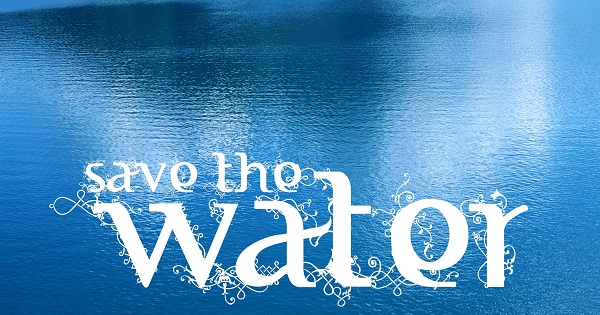
Categories | Foreign look, Various |
Go Green Font Edition from Fizzetica Type Foundry - Indonesia! -INDONESIA- Suatu kebanggaan bagi Fizz-Labz dan FTF merangkai huruf ini menjadi alfabet utuh dari a-z "lowerchase" dari logo pariwisata Visit Indonesia 2009, font ini bersifat free (free font) yang hanya boleh dipakai untuk pribadi, pendidikan dan bukan untuk kepentingan komersil. -ENGLISH- These fonts are free (free fonts) which should only be used for personal and not for commercial purposes. More info for commercial use ONLY: fizzlabz@gmail.com |